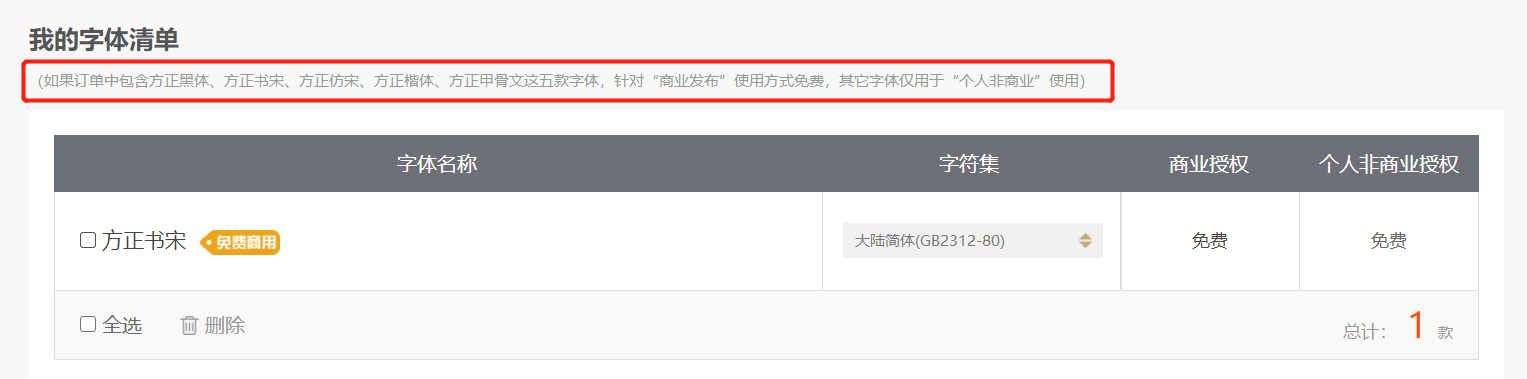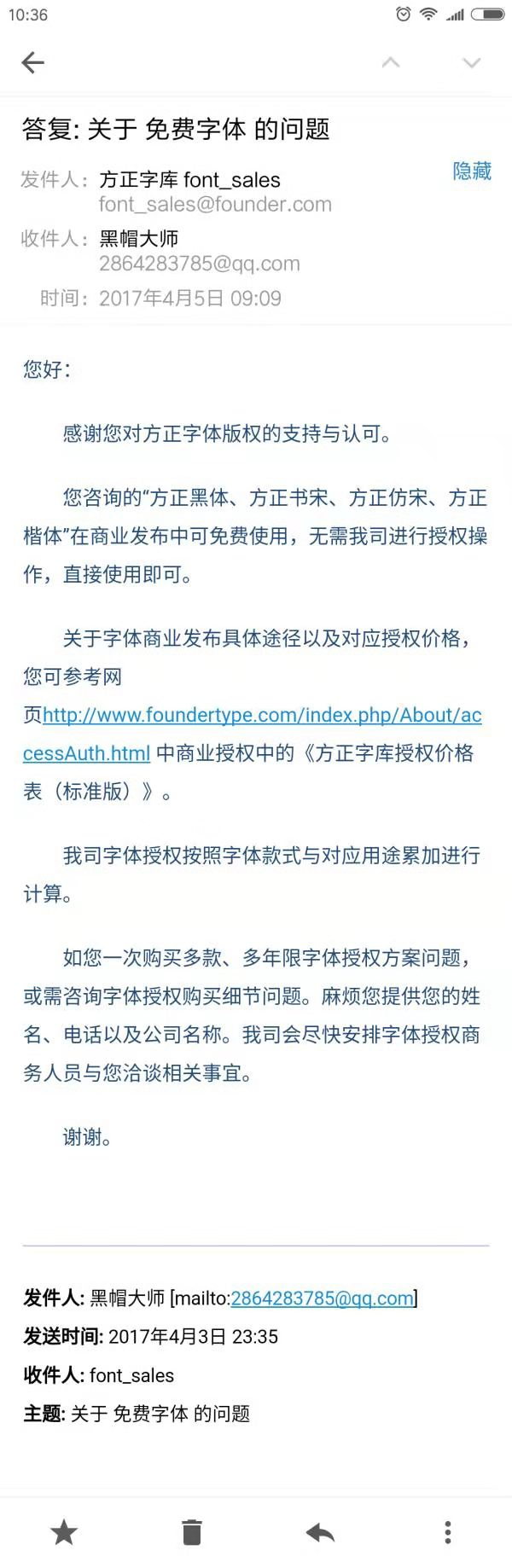
方正书宋源自上海印刷技术研究所的宋二,原字形距今已有近60年。最初的设计就是专门针对最常用的小字号正文排版。方正书宋的字形端正清秀,中宫适度。凭着清晰爽目、久读不易疲劳、印刷适性好的优点,长期被作为杂志和书籍的正文首选字体,所以也是一款非常经典的正文宋体。
方正书宋的字形端正清秀,中宫适度。凭着清晰爽目、久读不易疲劳、印刷适性好的优点,长期被作为杂志和书籍的正文首选字体